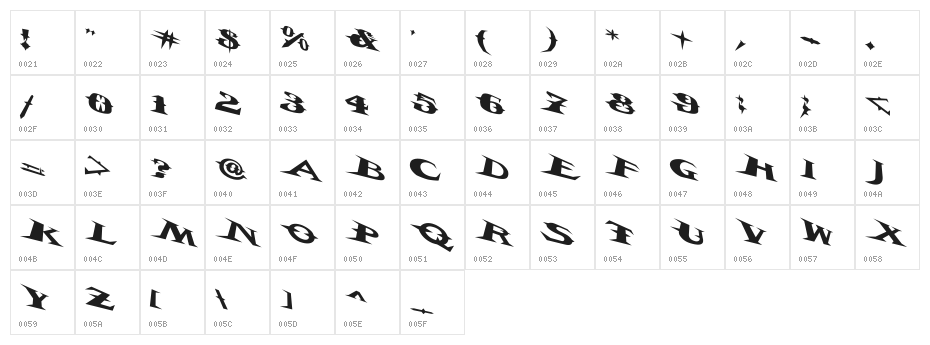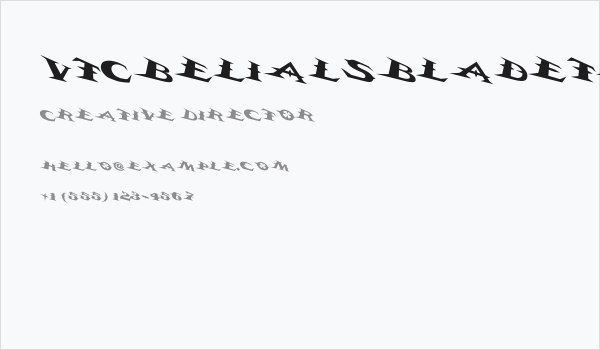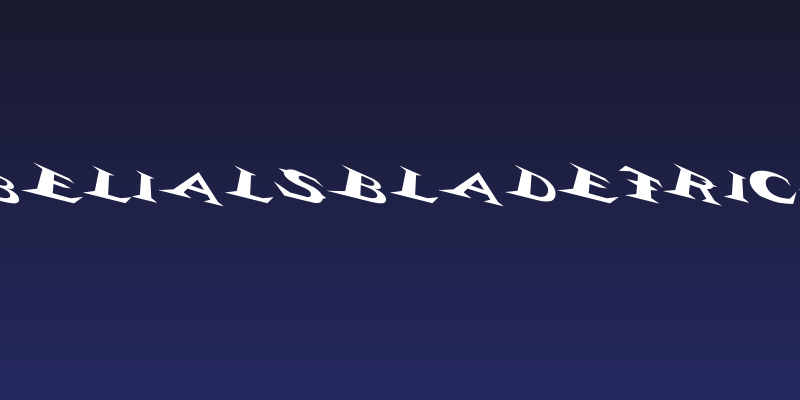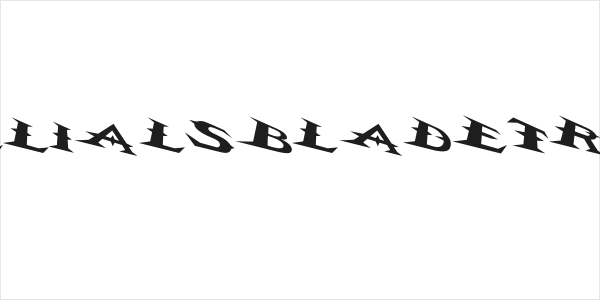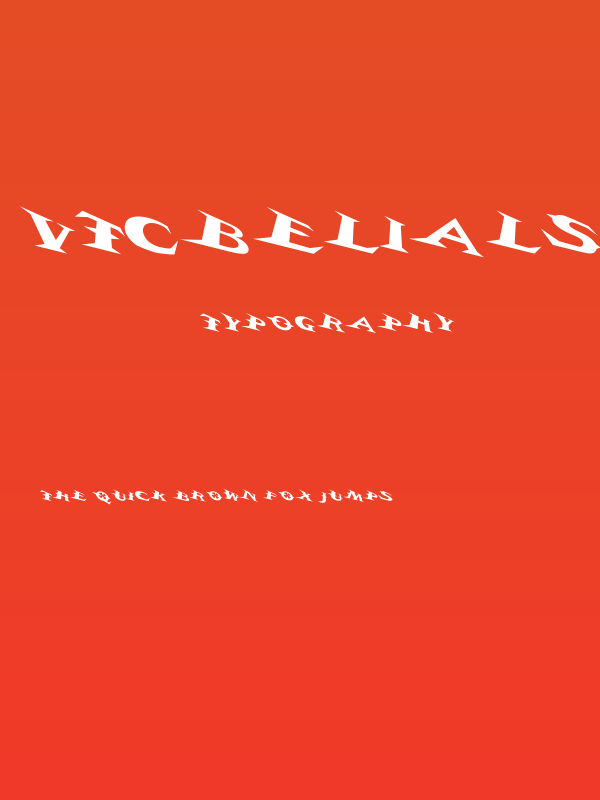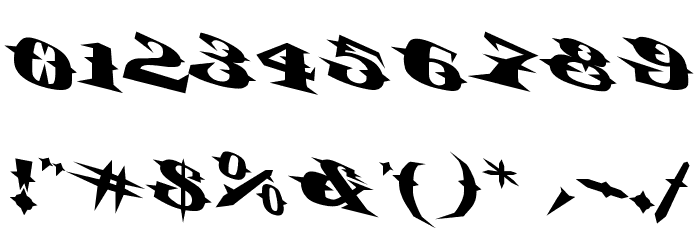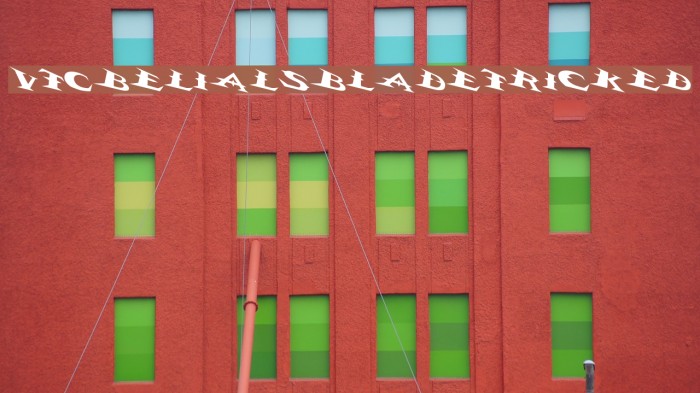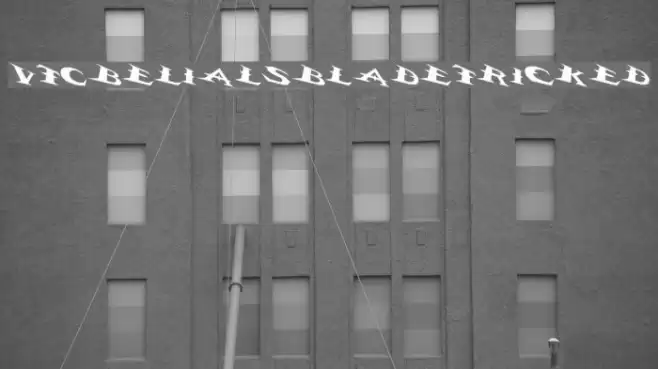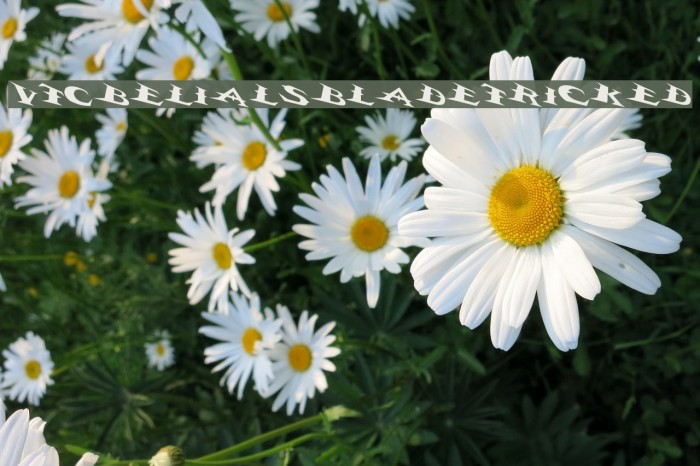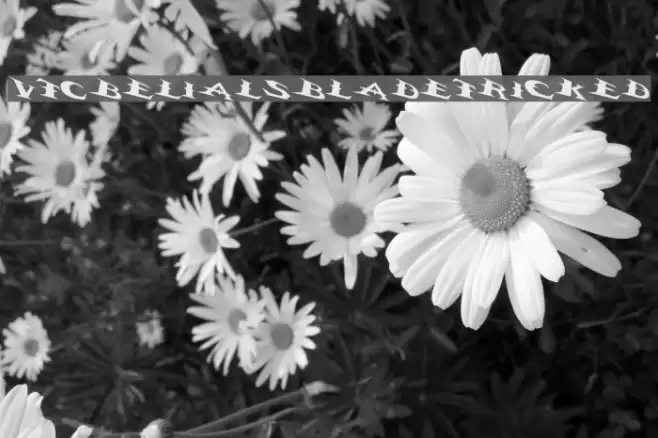
VTCBelialsBladeTricked Font
| Gesamtstil | Modern, Aggressive |
| Vorgeschlagene Projekte | Ideal for projects requiring a dramatic and intense aesthetic, such as video game titles, movie posters, or branding for extreme sports. |